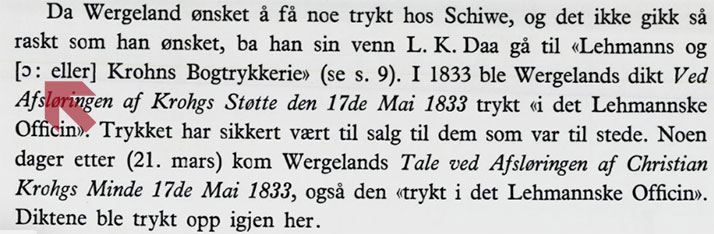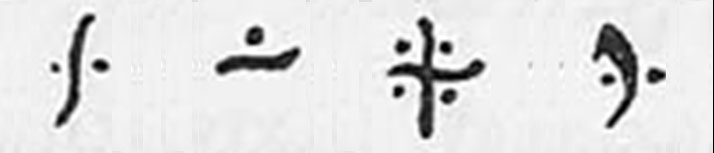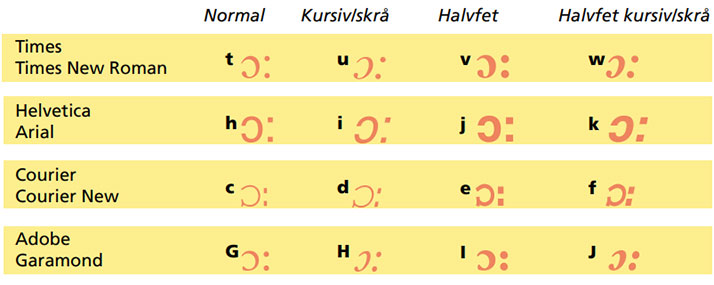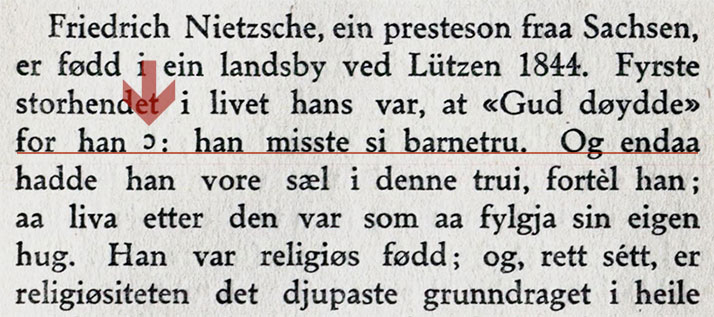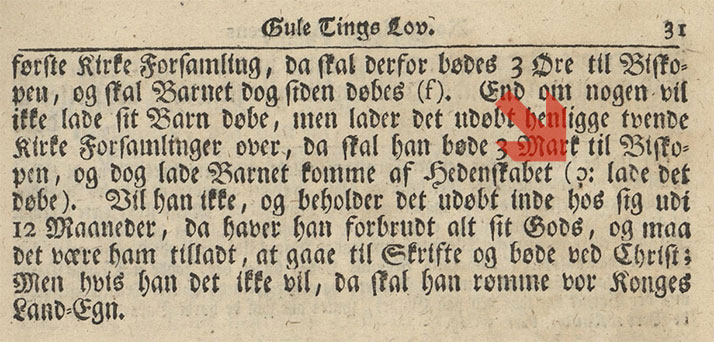
Inntil for noen tiår siden kunne man i norsk faglitteratur i blant finne en c snudd opp ned, etterfulgt av et kolon. Betydningen av dette var «det er», «det vil si», «det betyr». I dag er dette såkalte «forklaringstegnet» så å si ikke brukt. Men kanskje kunne vi ha behov for det? I typografiens «blytid» var det forholdsvis enkelt å rotere et tegn inne i en løpende tekst, mens det i dagens digitale typografi er mer komplisert. Men nå er løsningen her: en font med 16 forskjellige forklaringstegn er gratis tilgjengelig fra denne hjemmesida! Hvor kom forklaringstegnet fra, og hvordan er det blitt brukt? Den danske språkforskeren Rasmus Rask (1787-1832) skrev at forklaringstegnet er blitt brukt siden middelalderen, vesentlig i Danmark, Norge og Island, kun i liten grad i Sverige. Dets betydning er d.e. (det er) / i.e. (id est). Ifølge Rask er et lignende tegn blitt brukt i Nord-Italia - der var dets form først et kolon, deretter en c rotert 180 grader, så til slutt et nytt kolon.(1) Det eldste norske trykket jeg har sett som anvender forklaringstegnet, er fra 1751.(2) Det siste jeg har sett, der satsen er utført innenfor gammel teknologi med løse typer, er fra 1965. Ved håndsats og Monotypesats kunne en c snus opp ned for å lage dette tegnet, fordi disse satsartene var basert på løse typer. Men tegnet ville ikke alltid ligge vertikalt riktig i forhold til skriftlinjen. Dette avhang av den enkelte skrifts utforming (se eksemplet til høyre). Noen ganger overså man dette problemet, andre ganger har man nok valgt å file på typen og fylle ut med blindmateriell for å oppnå et tilfredsstillende resultat. Linotypesats var uegnet til å sette forklaringstegnet, fordi linjene i dette tilfelle ble støpt som en helhet. |
Forklaringstegnet (Adobe Garamond). Aars og Hofgaard: Norske retskrivnings-regler med alfabetiske ordlister (1907) (over) er den første norske kilden jeg kjenner som gir tegnet et navn, altså «forklaringstegn». Se stor versjon her. (1) Jeg har ikke selv sjekket denne kilden, og har heller ingen referanse. (2) Hans Paus: Samling af gamle norske Love fra 1751. Se den her. Takk til Per-Erik Skramstad for denne referansen.
Forklaringstegnet ble omtalt i Kirstes yrkeslære for settere, helt fram til dens tredje og siste utgave i 1965. Dette var den viktigste læreboka for typograflærlinger og yrkesskoleelever fram til 1980-tallet. Her heter det: «Forklaringstegn er en omvendt c. Den blir ofte brukt i norsk sats istedenfor d. e. = det er. En passer på at den omvendte c står på linje, ellers setter en d.e.» Det er interessant at det står at det blir brukt i «norsk» sats, hvilket understreker at tegnet ikke var utbredt internasjonalt. Legg også merke til at det anbefales å ikke bruke tegnet hvis det ikke blir et estetisk tilfredsstillende resultat. Har tegnet et bruksområde i dag? Ved gjengivelse av gamle tekster i ny, digital sats (ikke i fotografisk faksimile), vil det være nødvendig å rekonstruere tegnet. Dette er gjort f.eks. i Ivar Aasen: Norske ordtak (4. utg. 2003), og det er oppnådd en korrekt gjengivelse av originalen. Også i moderne utgivelser kan det være formålstjenlig å bruke tegnet. Ikke minst i oppslagsverk, fordi tegnet er mindre plasskrevende enn å skrive d.e. eller dvs./d.v.s. I Kunnskapsforlagets Norsk ordbok (red. Tor Guttu), 2. utg. 2005, er tegnet brukt i en del ordforklaringer. Det blir der forklart å bety «det vil si». Forstår leserne tegnet i dag? De fleste i alderen over ca. 40 år har nok glemt det, men vil likevel sannsynligvis raskt forstå det, når de gjenser det. De yngre vil være ukjent med det, men jeg tror tegnets utforming vil lede dem intuitivt på rett spor i forståelsen av det. Jeg tror tegnet fortsatt har en framtid. Det er en typografisk detalj som ikke bør gå i glemmeboka. Jeg har derfor laget den gratis skrifttypen «Forklaringstegn» i TrueType- og PostScript Type1-format for Mac og PC. Her finner man forklaringstegn for skriftene Times/Times New Roman, Helvetica/Arial, Courier/Courier New og Adobe Garamond, i de fire snittene normal, kursiv/skrå, halvfet og halvfet kursiv/skrå. Værsågod, og lykke til. Jeg vil være takknemlig hvis de som har ytterligere informasjon om dette tegnet vil kontakt meg. |
I skriften Genzsch antiqua (Nordisk antikva) ble ikke c-en liggende på skriftlinja etter at den var rotert. Se stor versjon her. (Fra Arne Garborg: Straumdrag, 1920) FLERE EKSEMPLER PÅ BRUK AV FORKLARINGSTEGN: Normalsnittet av forklaringstegnet i Times, Helvetica, Courier og Adobe Garamond. Disse er nå tilgjengelige i en gratis skrifttype. |
ETTERSKRIFT 1 En leser har gjort meg oppmerksom på at den snudde c finnes i Unicode-tegnsettet. Mer nøyaktig i Unicode-blokken «IPA Extensions», som er et tegnsett for lydskrift. Tegnet heter «Latin small letter open o» og har identifikasjonen U+0254. Forklaringstegnet kan dermed settes sammen av dette tegnet og et kolon, hvis man har den nødvendige skrifttypen installert. Leseren nevner følgende skrifttyper med dette tegnet: |
Forklaringstegnet er her sammensatt av to tegn, i skrifttypen Junicode regular. Det er en Garamond-variant. |
| ETTERSKRIFT 2
Tegnet er brukt i «Norsk rettskrivningsordbok», Kunnskapsforlaget 1985, og på bokas forsats er det trykt en oversikt over «Tegn og symboler som brukes i norsk». Her er forklaringstegnet med dets navn og betydning er angitt slik: «(scilicet, uttalt skiliket), det vil si». Ifølge internett betyr scilicet «that is to say», «namely», «das heisst», «nähmlich». Det springer ut av det latinske «scire licet» (it may be known/it is permitted to know). Det forkortes sc eller ss. Jeg finner ingen informasjon om at det kan ha den grafiske uttrykksformen som er blitt brukt i Norge. Derimot er det et initiativ for å få det inn som eget tegn i Unicode, i formen lang s med en skrå strek gjennom («latin small letter s with bar across»). Det henvises til at det har vært brukt i Old English. |
| ETTERSKRIFT 3
Enda en leser har gjort meg oppmerksom på tre skriftfamilier med det han kaller en omvendt c: Charis SIL, Doulos SIL og Gentium - http://scripts.sil.org/ |
English summaryThe combination of a c turned upside down and a colon was until 30-40 years ago used in Norwegian (and Danish) typography, meaning «i.e.»/«meaning». It was called, translated into English, «the explanatory symbol». The symbol fell out of use when common composition technique changed from handling single metal types to photocomposition, and later digital typsetting. The symbol also has a purpose today: it is narrower than the alternatives, and can reduce the length of copy. I have made a free typeface with the explanatory symbol in four diffent fonts - in 16 different styles. Please contact me if you know more about this symbol, as I would like to know more about its history and its use. Publisert første gang 2006-08-02 |